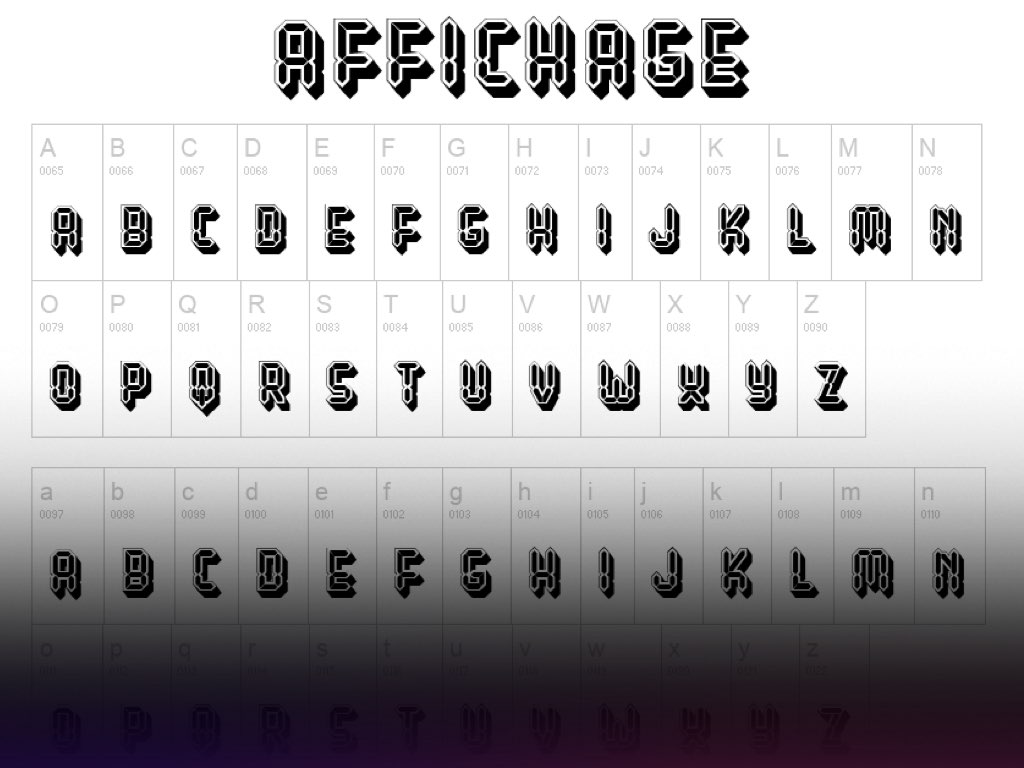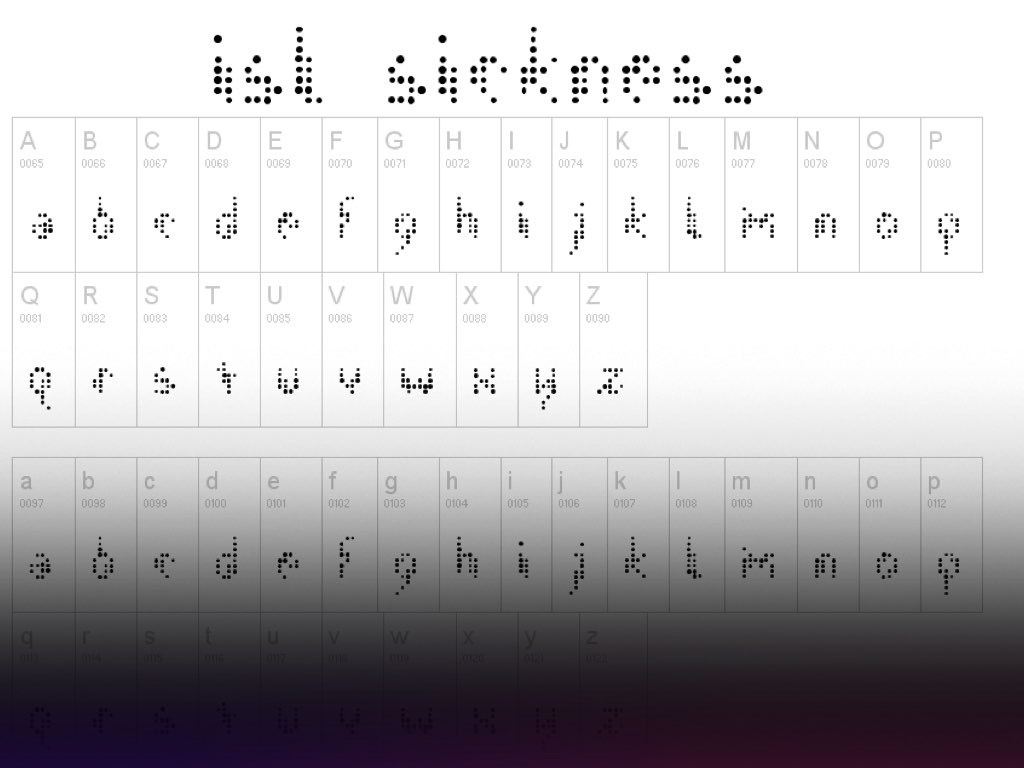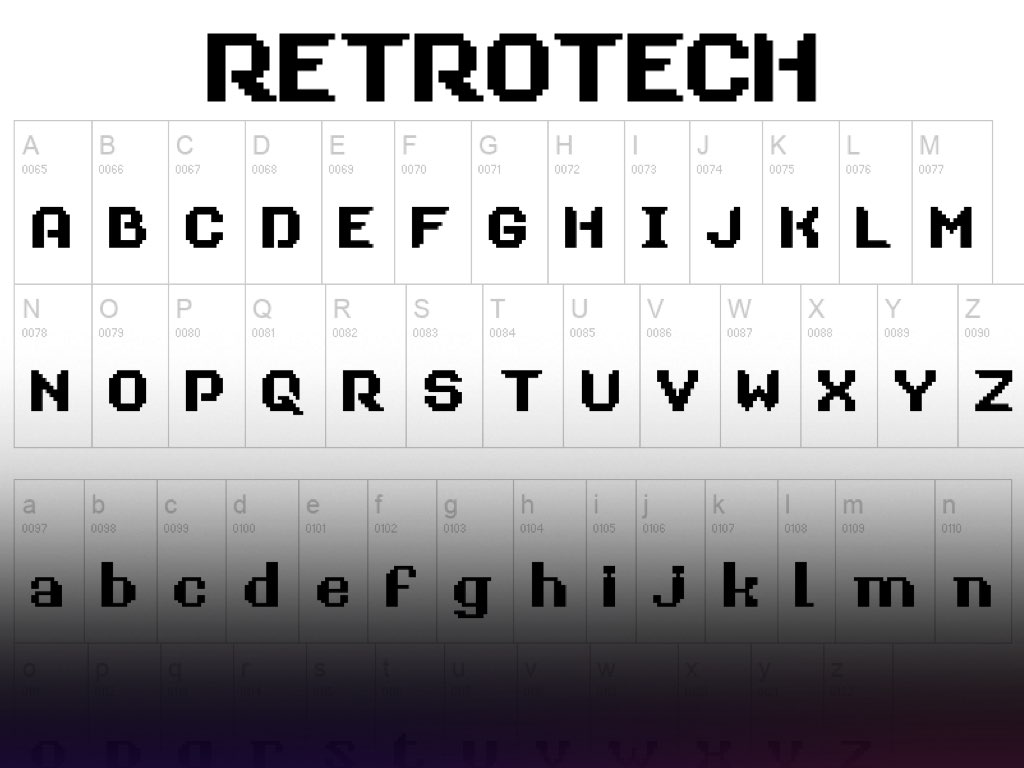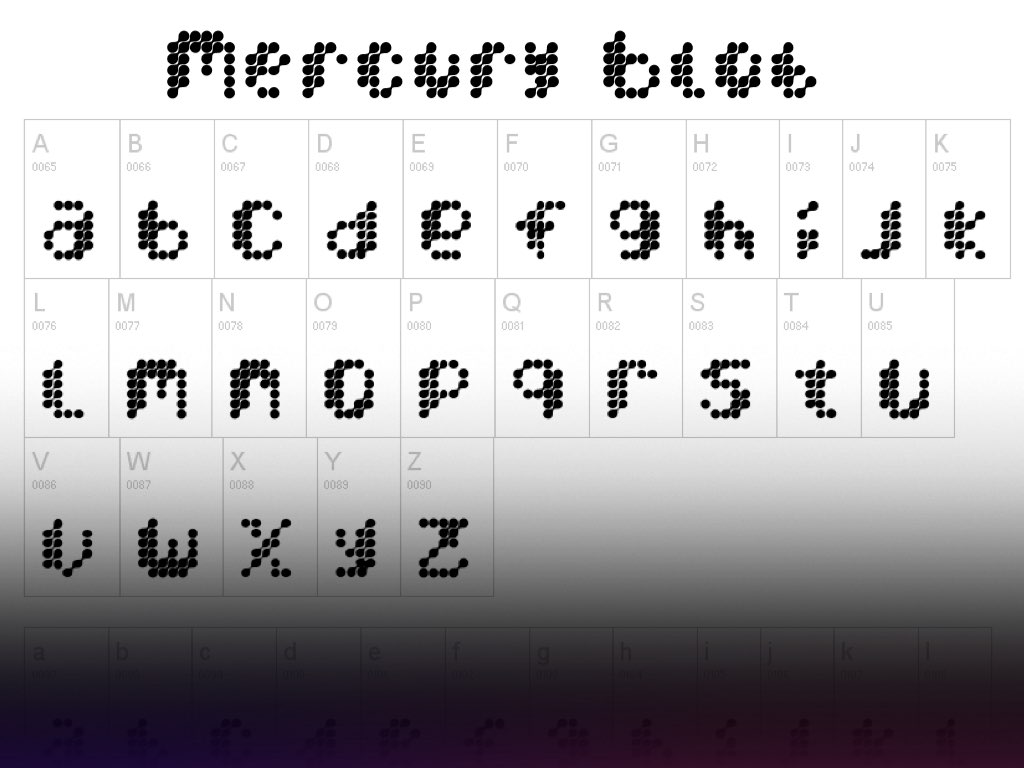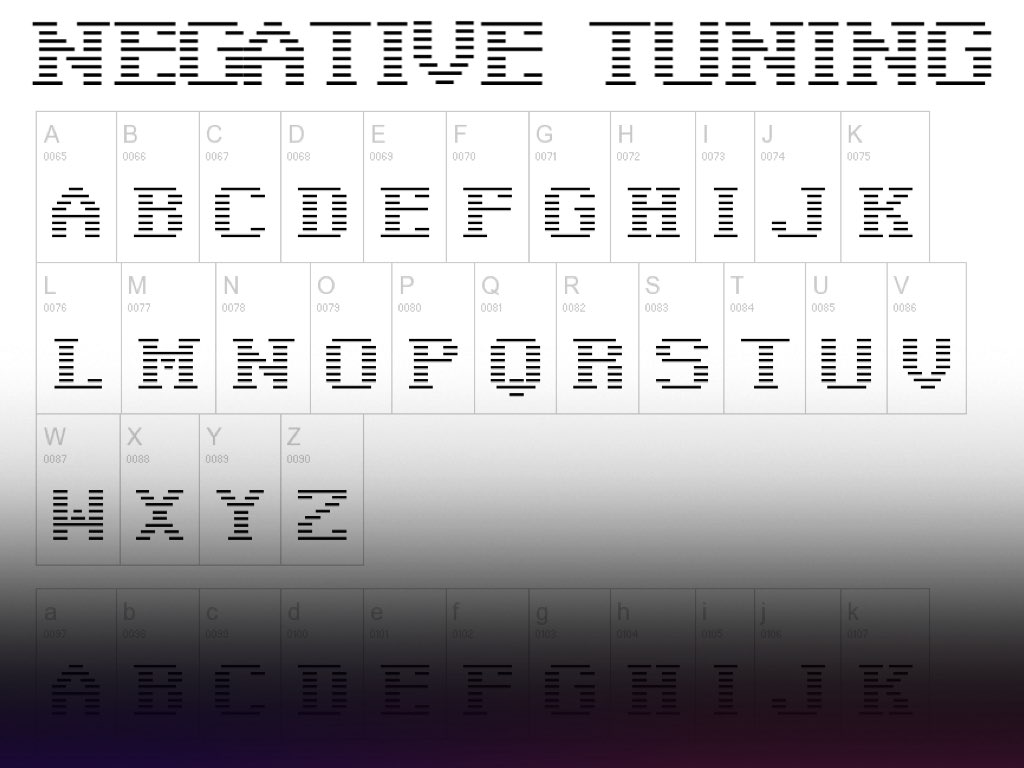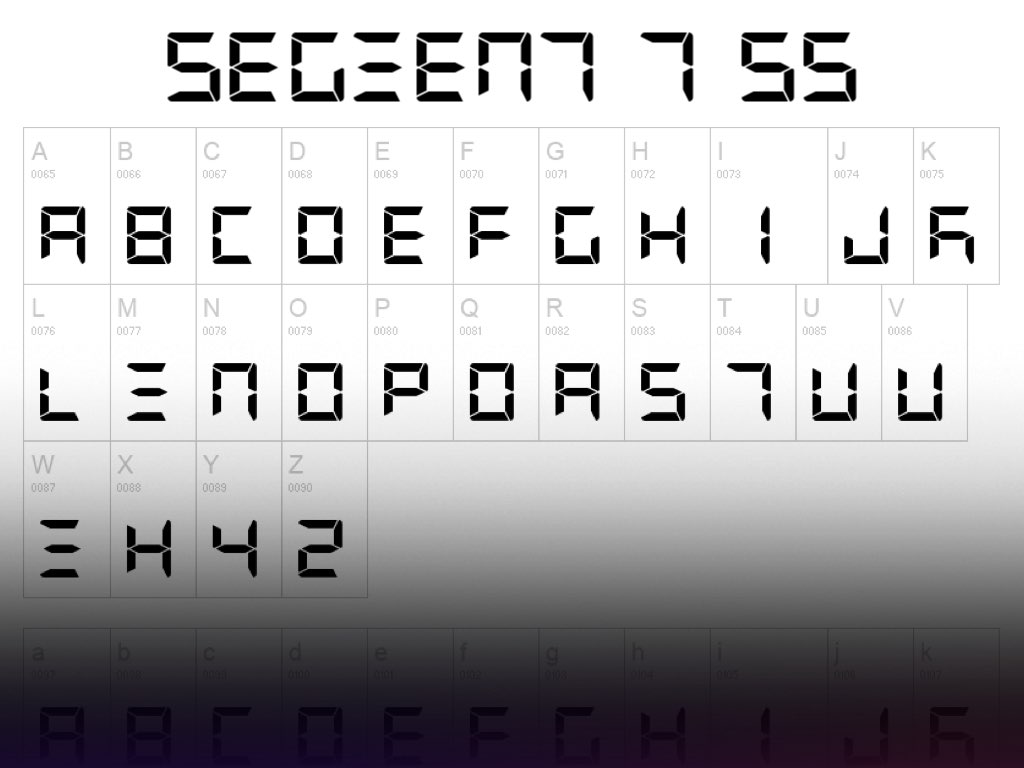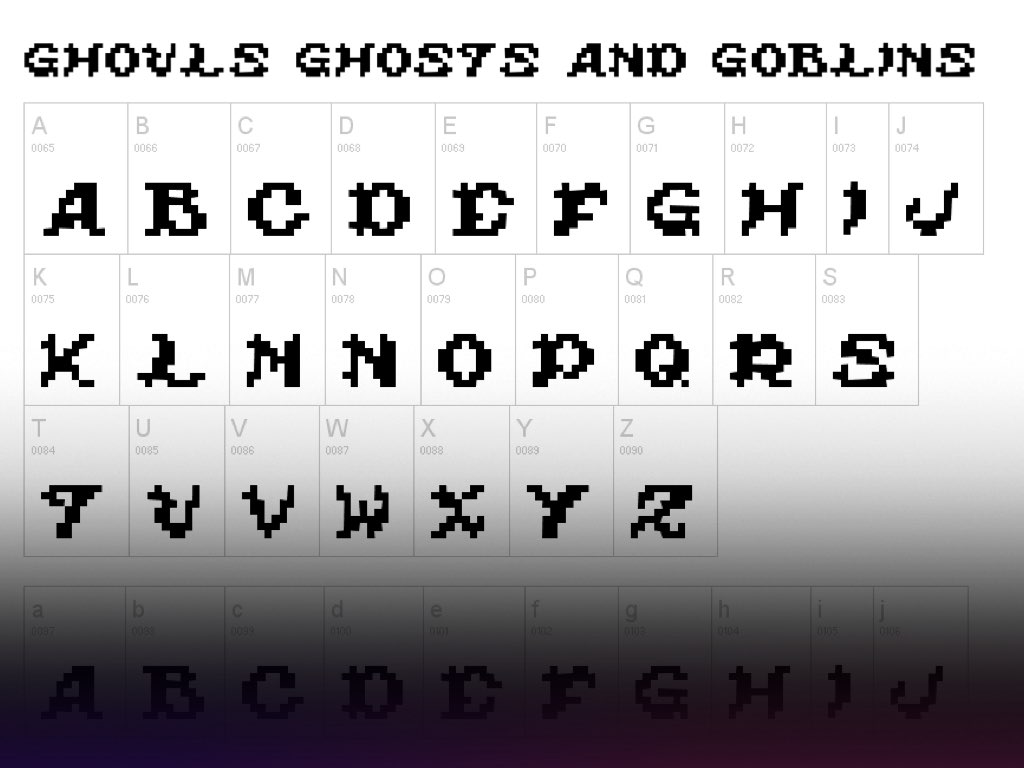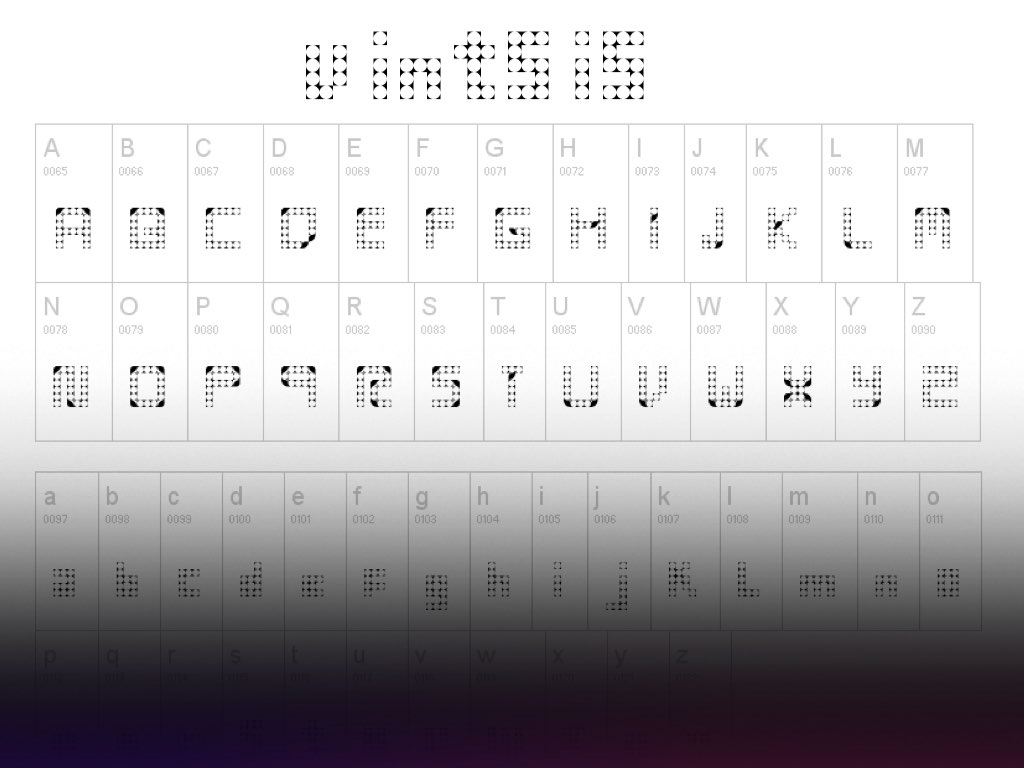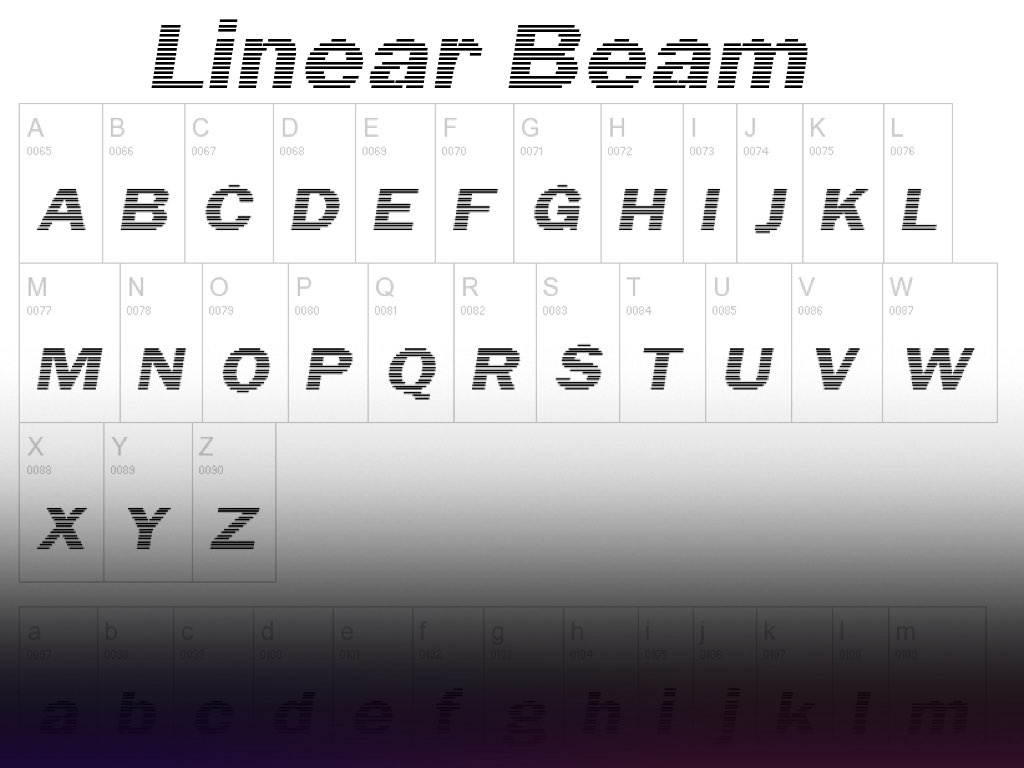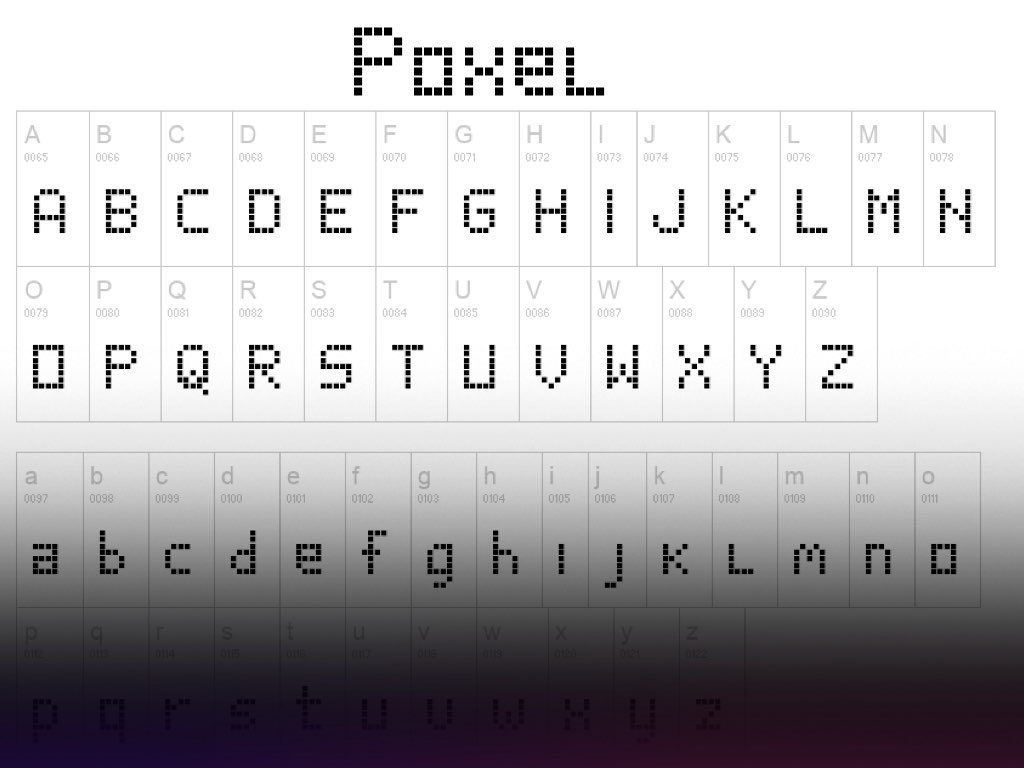
รวม 30 ฟอนต์ (Font) ย้อนยุคเท่ๆ โหลดฟรี!
ฟอนต์ย้อนยุคเป็นที่นิยมอย่างมากในปัจจุบัน ด้วยเสน่ห์แบบย้อนยุคที่ผสมผสานกับความทันสมัย ฟอนต์เหล่านี้เหมาะอย่างยิ่งสำหรับการเพิ่มลูกเล่นให้กับงานออกแบบ จะมีสไตล์ไหนบ้างไปดูกันเลย
ย้อนรอยความคลาสสิก กับฟอนต์สไตล์ LCD ที่จำลองความรู้สึกของจอ LCD ยุค 90 สามารถดาวน์โหลดและใช้งานได้โดยไม่ต้องเสียค่าใช้จ่าย เหมาะสำหรับนักออกแบบ นักเรียน นักศึกษา หรือบุคคลทั่วไปที่ต้องการเพิ่มลูกเล่นให้กับงานของตัวเองสามารถนำมาใช้งานได้เบื้องต้น และอย่าลืมตรวจสอบลิขสิทธิ์ก่อนใช้งานเชิงพานิชย์จะมีสไตล์ไหนบ้างไปดูกันเลย
1.Retrotech
2.G7 Segment 7 S5
3.Alarm Clock
4.Linear Beam
5.Dot Matrix
6.Karmatic Arcade
7.PixelSplitter
8.Poxel
9.Super Mario 85
10.Pil Love
11.Neonize
12.Electronic Highway Sign
13.The 2K12
14.Loopy
15.Round
16.Citaro Voor
17.Ring Matrix
18.FixCystNeon
19.Corrupt Pixel
19.Mode X
19.Wi/5Med Grid
20.JD DigiSquare
20.Chlorenuf
21.7 Inch
22.Imajix 9dot
22.Orb!
24.LED Real
24.Patopian 1986
25.Affichage
26.Mercury Blob
27.Negative Tuning
28.SL Sickness
29.Ghouls Ghosts and Goblins
30.Vintsis